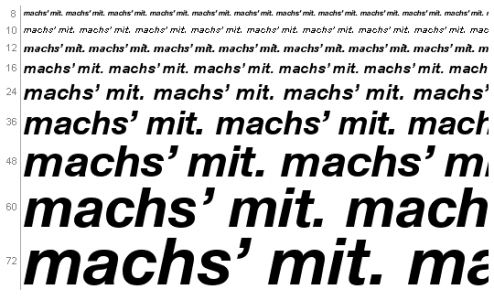
mach's mit und Gib Aids keine Chance
Könnt ihr mir die Namen der Schriften nennen?
Ist das bei dem Gib Aids keine Chance Logo eine linear Grotesk oder täuscht das? Haben die Designer die Buchstaben bei dem GIB gequetscht oder warum sehen die so anders aus als beim Rest?
Bei dem mach's mit Logo ist das ein echter kursiver Schnitt oder haben die Designer das einfach schräg gestellt?
Mh, also die futura condensed habe ich nicht hier, aber die anderen Schnitte passen mit dem Apostroph nicht. Bei der Helvetica das gleiche. Ich mutmaße es könnte die Eurostile sein, aber ich habe keine Möglichkeit es zu überprüfen. Fontshop will mir das Apostroph nicht anzeigen.